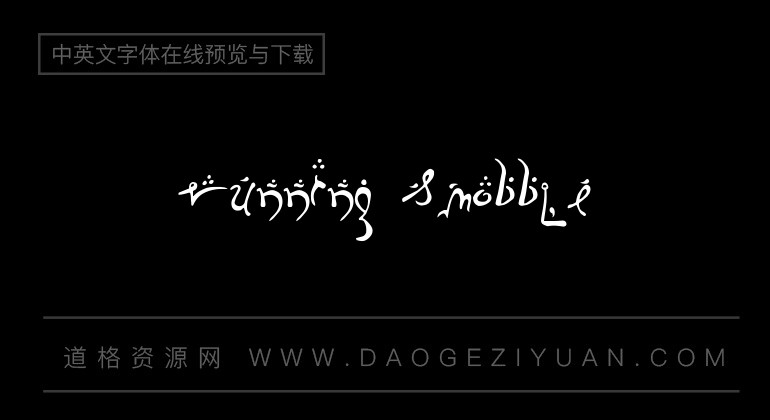
Running Smobble
? Running Smobble字体是一款拥有明亮活泼的外观的字体,它具有优雅的曲线和流畅的线条,使文字看起来更加生动有趣。它的特点是拥有轻松的型态,更加流畅,更容易阅读。它适用于各种类型的文字,可以用于印刷和屏幕上的应用。此外,它还具有多种字体样式,可以满足不同的设计需求。
Running Smobble是一款非常不错的手写艺术字体,具有很好的视觉感,适合于文化类的宣传设计、商业类品牌的广告和产品包装设计以及个性化文字排版等较多场景。